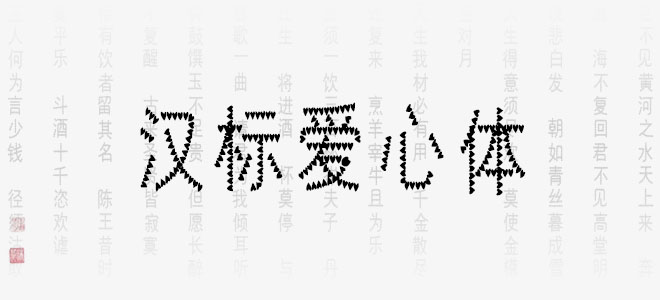
漢標(biāo)愛心體筆畫全部以心形圖案制作,簡潔流暢,單純可愛,化點為心,朝氣蓬勃,溫婉動人,字里行間藏不住的愛心,滿滿的少女氣質(zhì)。適用于文藝類的書刊、品牌廣告和產(chǎn)品包裝設(shè)計,以及社交網(wǎng)絡(luò)的個性化用字。歡迎喜歡漢標(biāo)愛心體的朋友前來下載使用。
漢標(biāo)愛心體